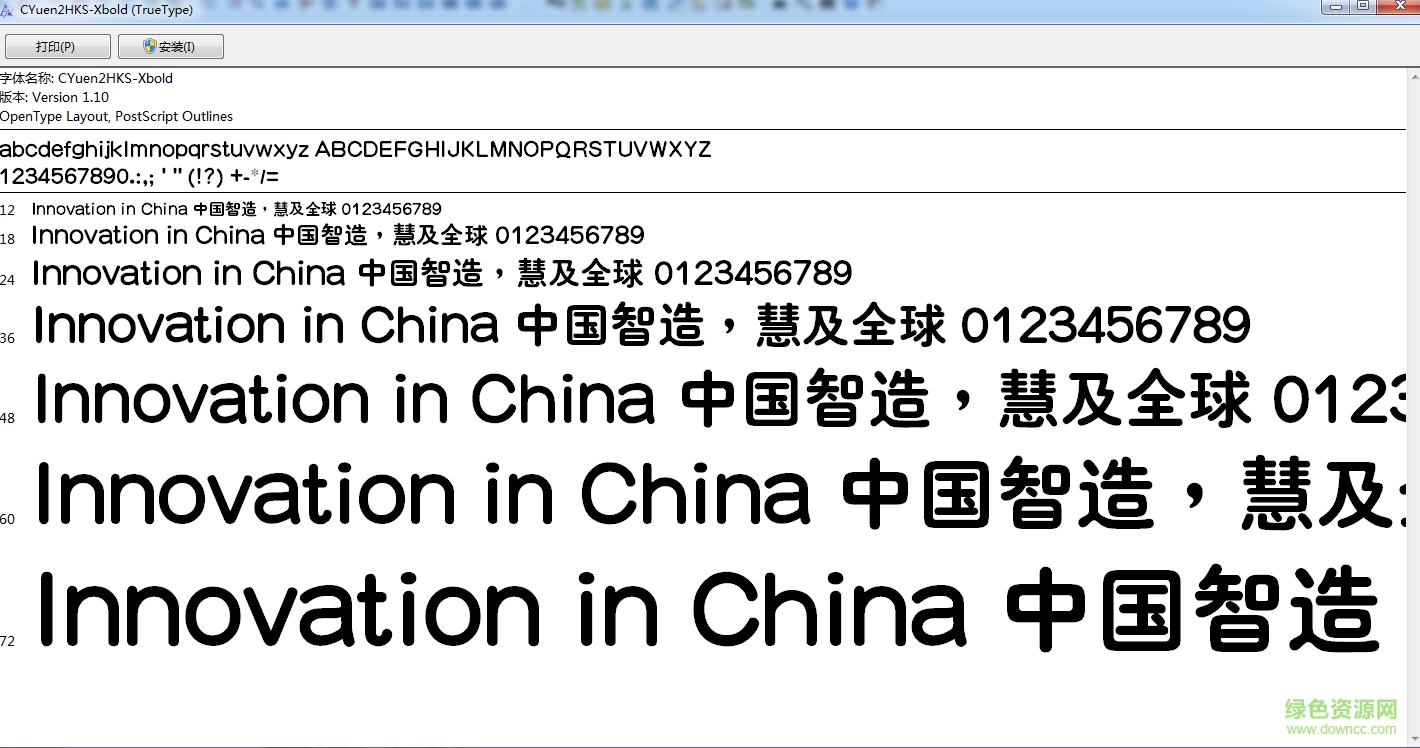
cyuen2prc字體是一款十分符合構(gòu)形規(guī)律的精美英文字體,該字體筆法典雅,形態(tài)工整,骨絡(luò)干凈分明,適合排版設(shè)計使用,需要的朋友快來綠色資源網(wǎng)下載吧!
粗壯渾厚、莊重嚴(yán)肅,表現(xiàn)力強(qiáng)。宜用于文章、報刊的大標(biāo)題,也可作廣告用字。